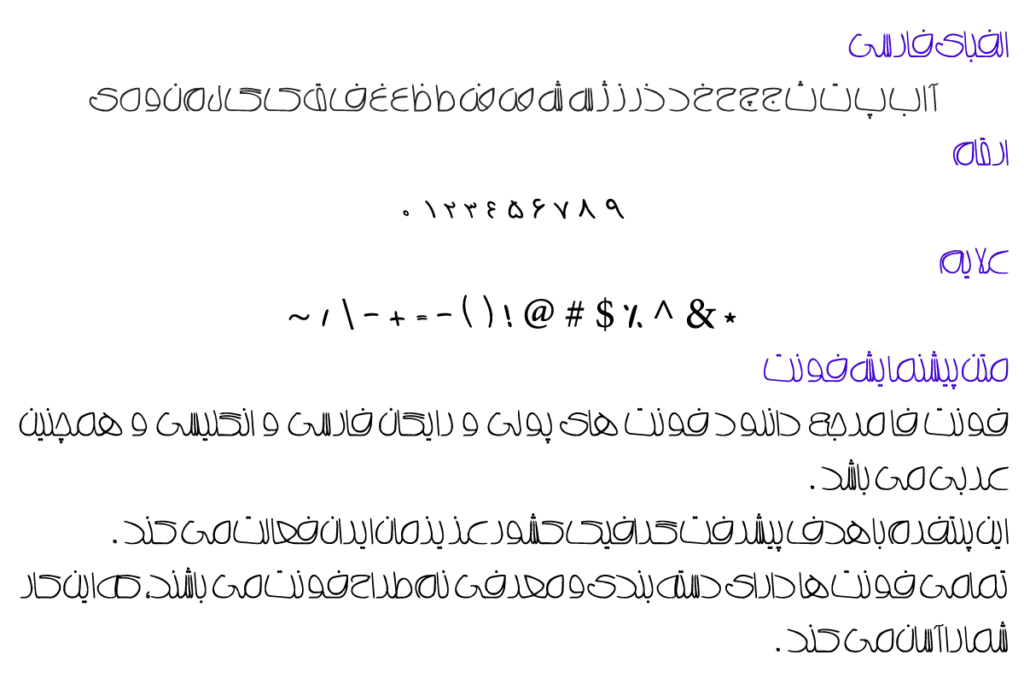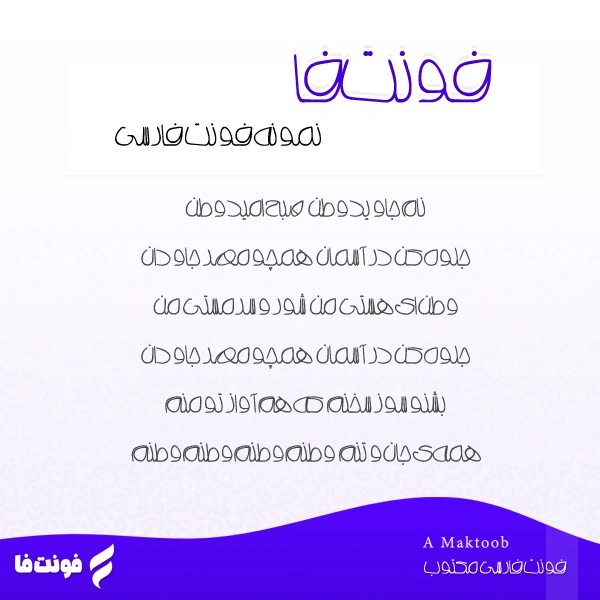
فونت فارسی مکتوب – A Maktoob
نوع فونت: فونت دست نویس
توضیحات و معرفی فونت مکتوب
فونت فارسی مکتوب ( A Maktoob ) از مجموعه فونت های آزاد می باشد، همینطور نوع فونت دست نویس می باشد.
فونت زیبای مرتبط در سال 1390 طراحی و ساخته شده است.
در تصویر زیر، پیش نمایشی از این تایپ فیس را همراه با شعر زیبای فارسی میبینید.